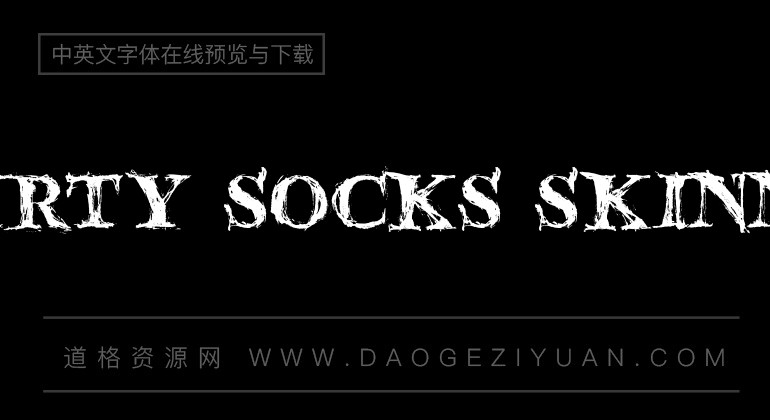
Dirty Socks Skinny 是一种手写风格的英文字体,由设计师 David Kerkhoff 开发。这种字体采用了细线条和不规则的笔画,给人一种随意和自然的感觉。在设计中,Dirty Socks Skinny 字体借鉴了涂鸦和手写字体的风格,使它看起来更加有趣、生动和富有个性。 此外,Dirty Socks Skinny 字体也具有非常广泛的应用领域。它适用于海报、标志、印刷品、包装设计、网站设计和广告等各种设计领域。这种字体的设计风格独特,能够吸引人们的注意力,并且在与其他设计元素配合时能够产生出极具冲击力的效果,使得它成为设计师们的首选之一。内容介绍
Dirty Socks Skinny是一款非常不错的手写艺术字体,具有很好的视觉感,适合于文化类的宣传设计、商业类品牌的广告和产品包装设计以及个性化文字排版等较多场景。